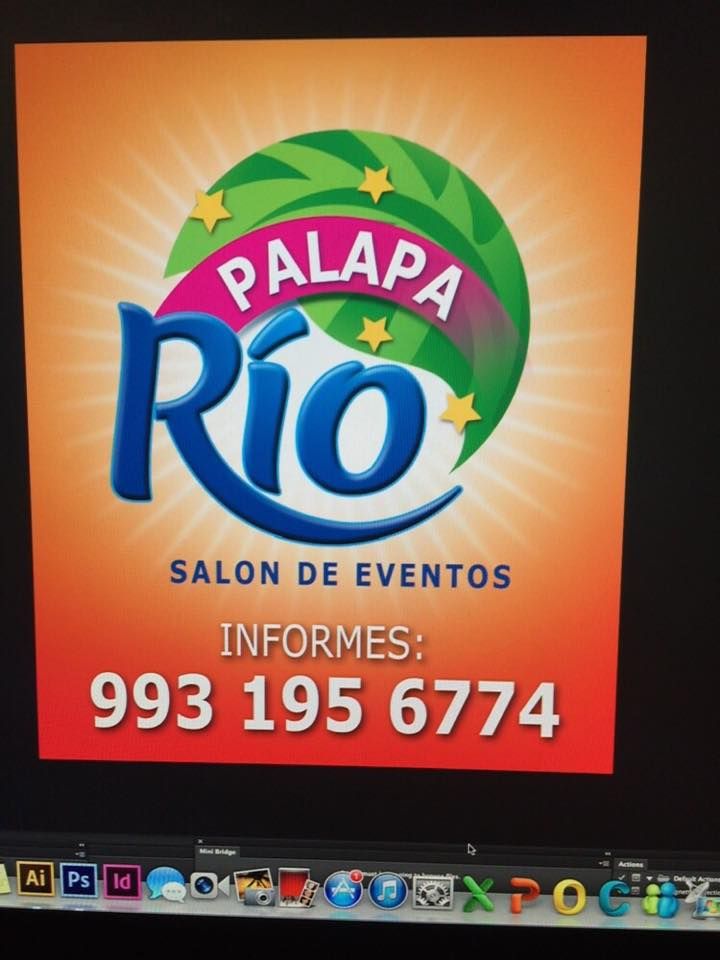
Opino lo mismo que @1236.
De todas formas, si quieres hacer algo así para un proyecto personal pero te da palo dibujar lettering, siempre podrás usar una tipo en plan handwritten, (Pacifico o Kaushan Script en Google Fonts, por ejemplo, son del estilo).
Tiene pinta de ser un lettering hecho expresamente para el logo.